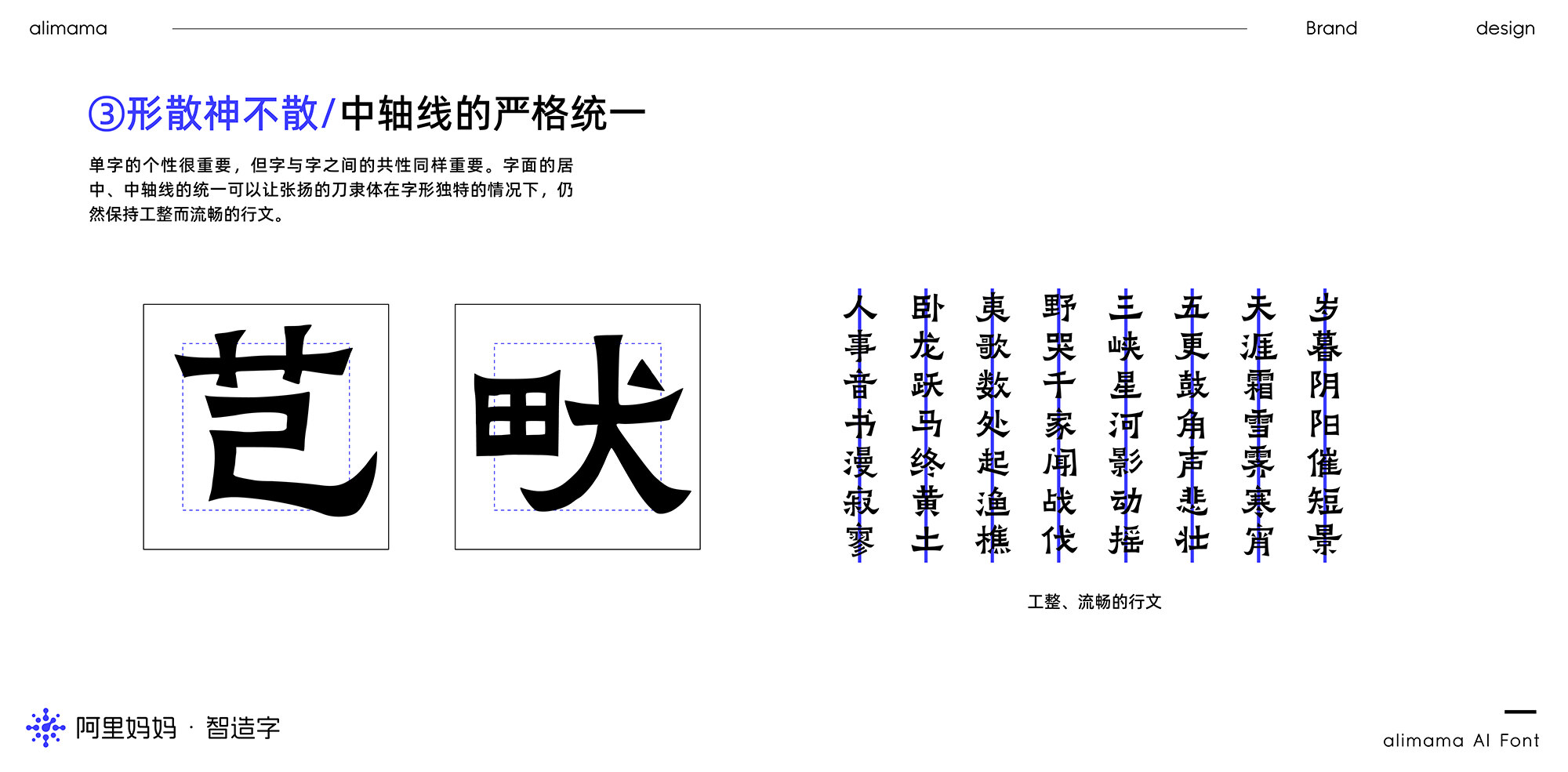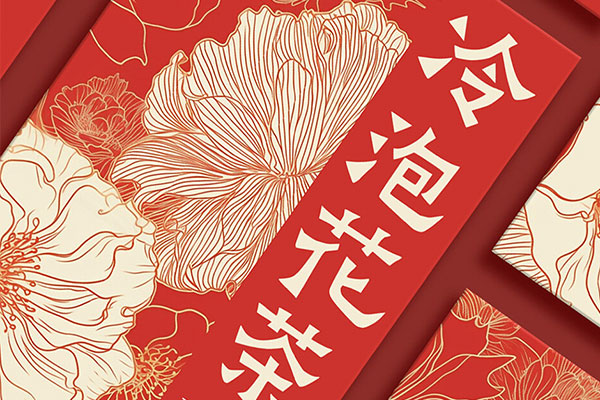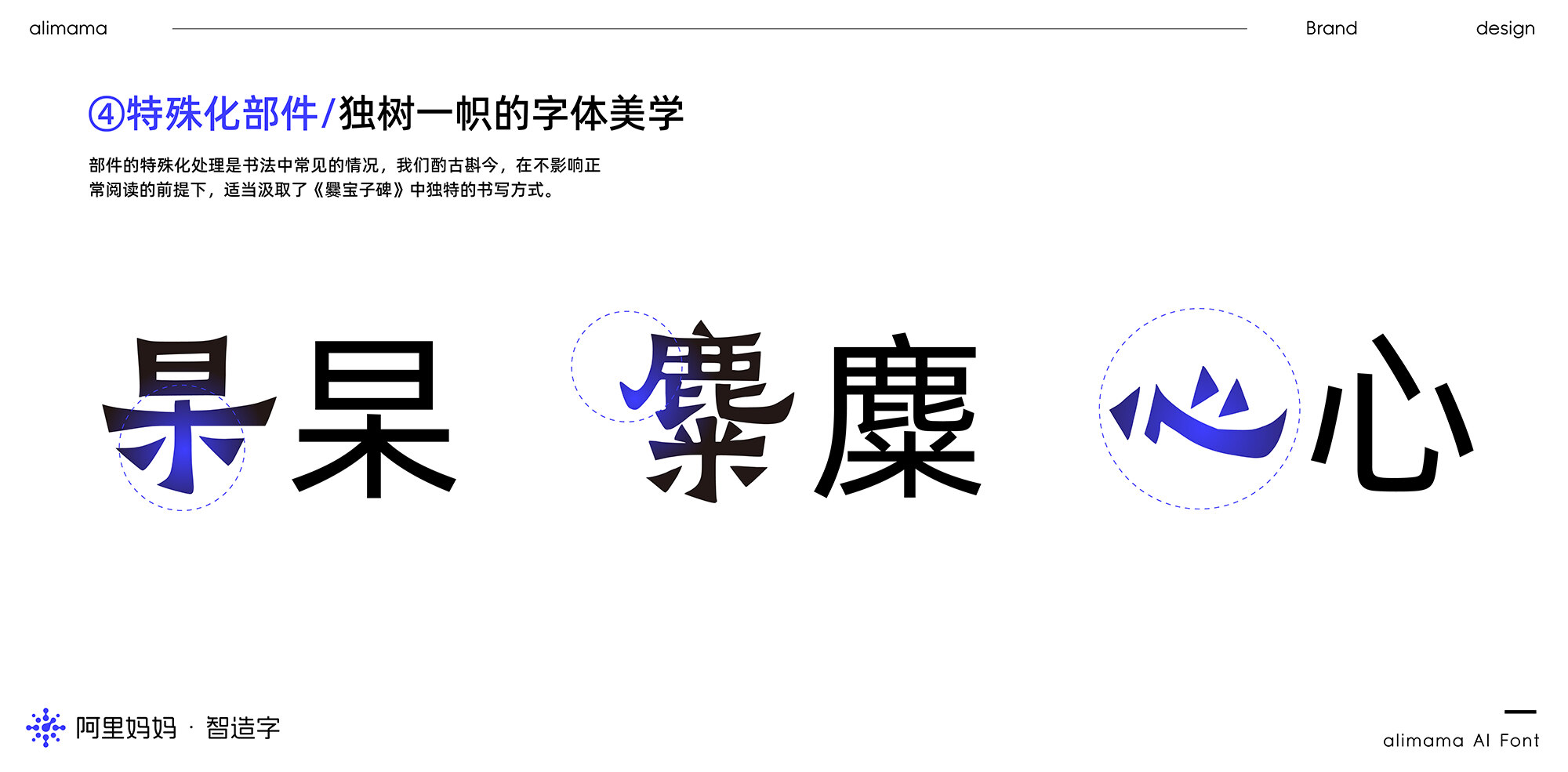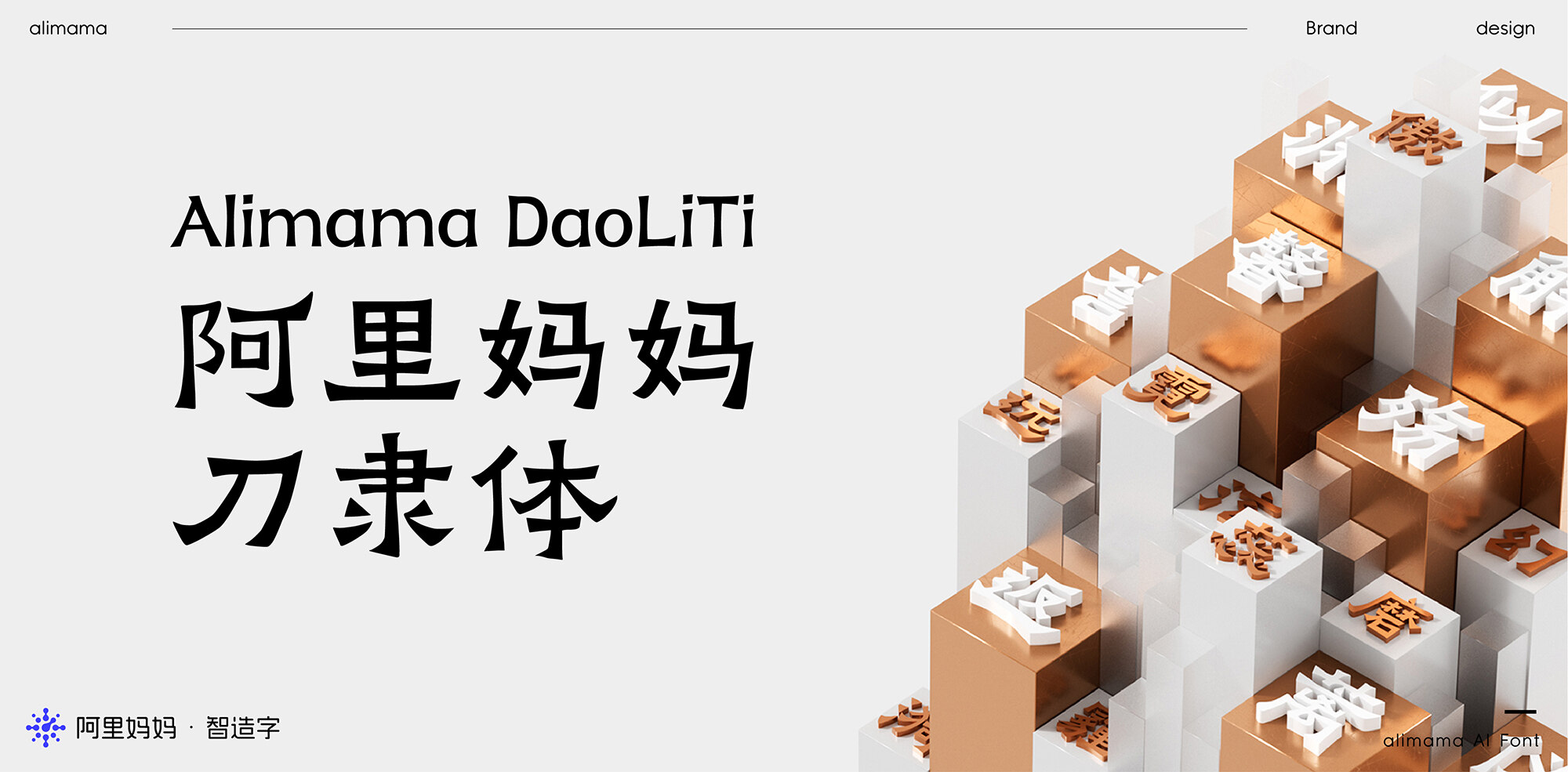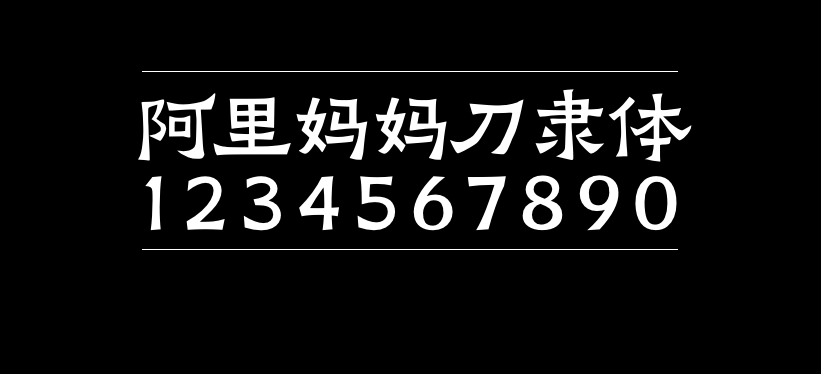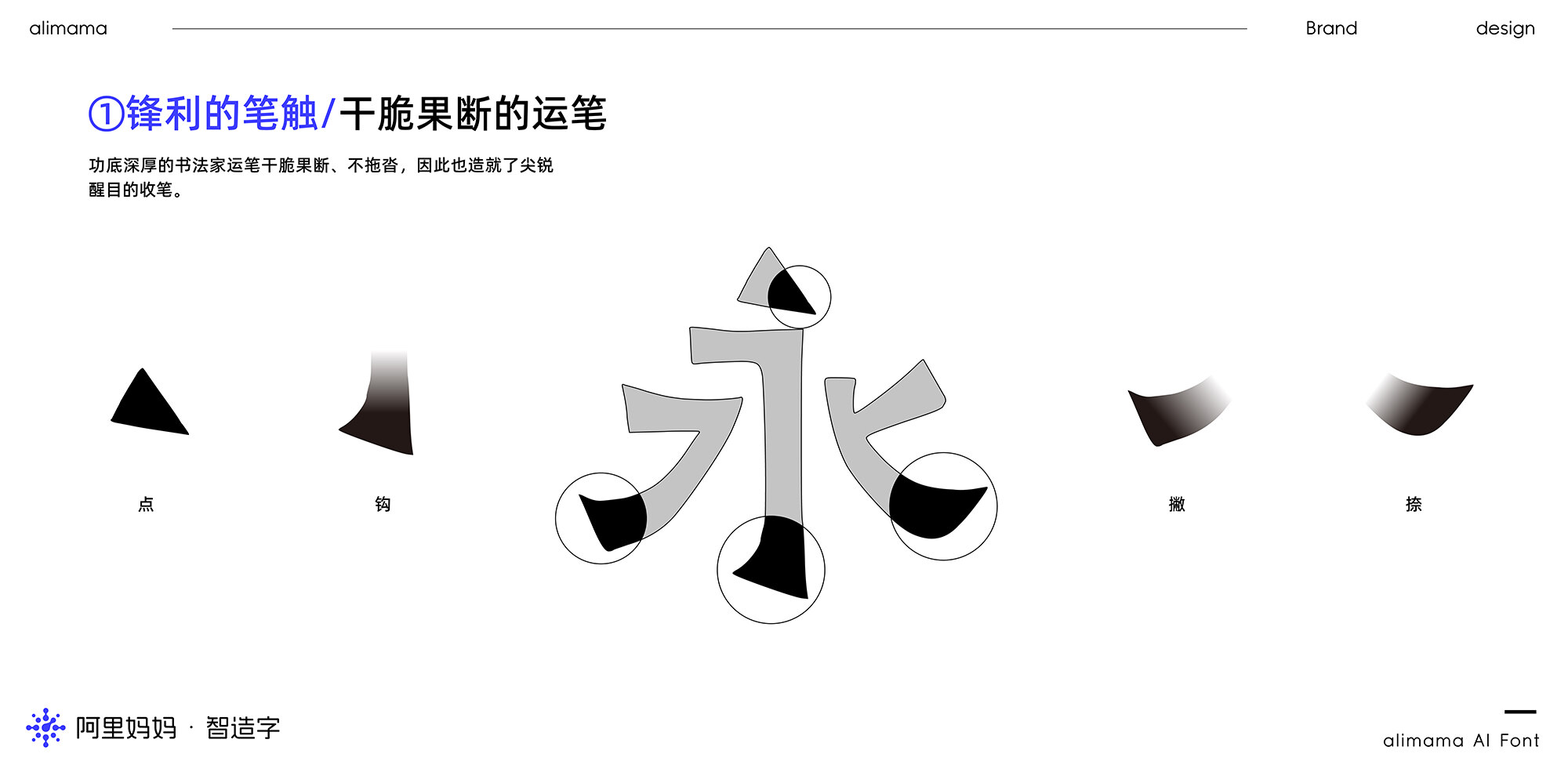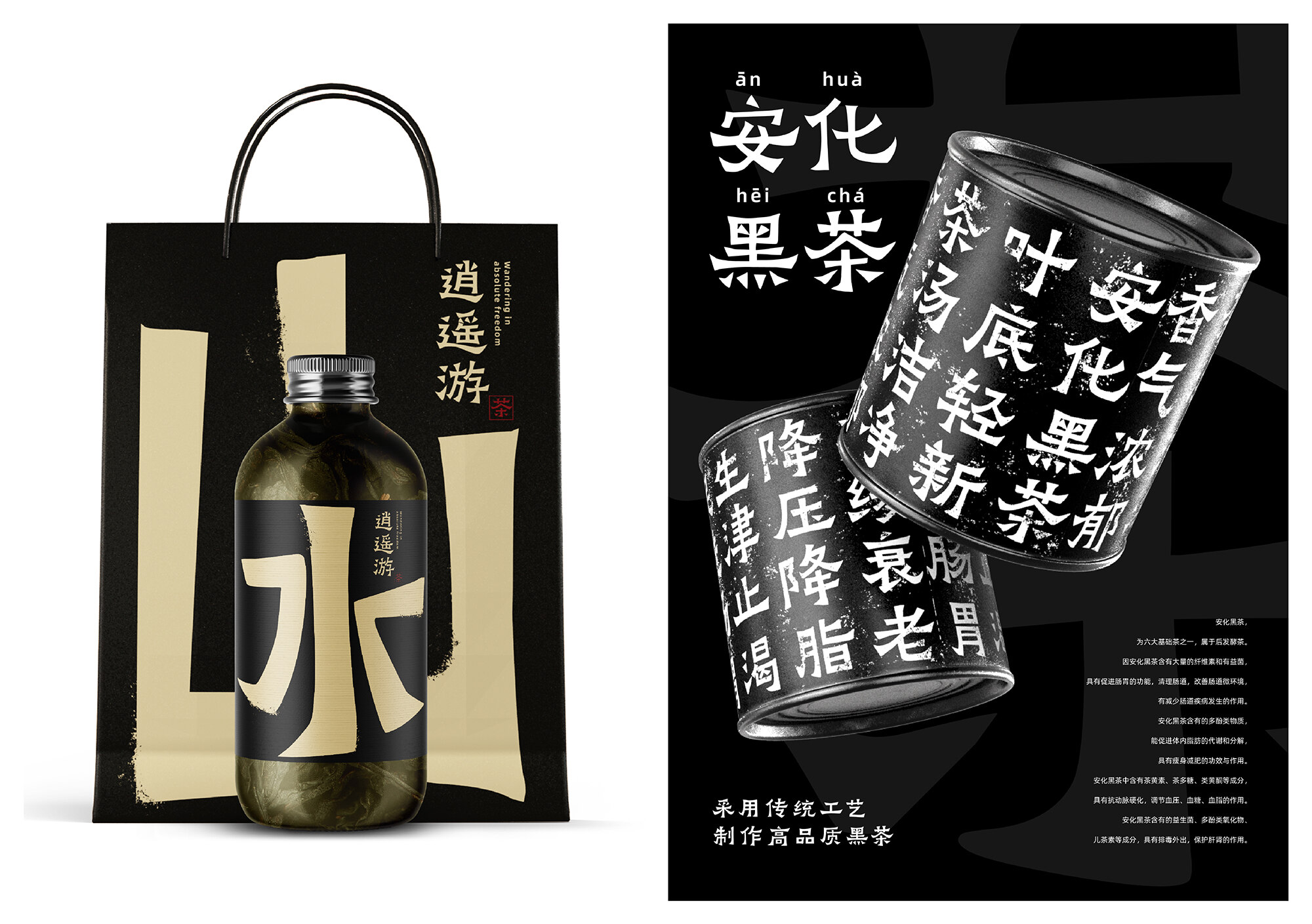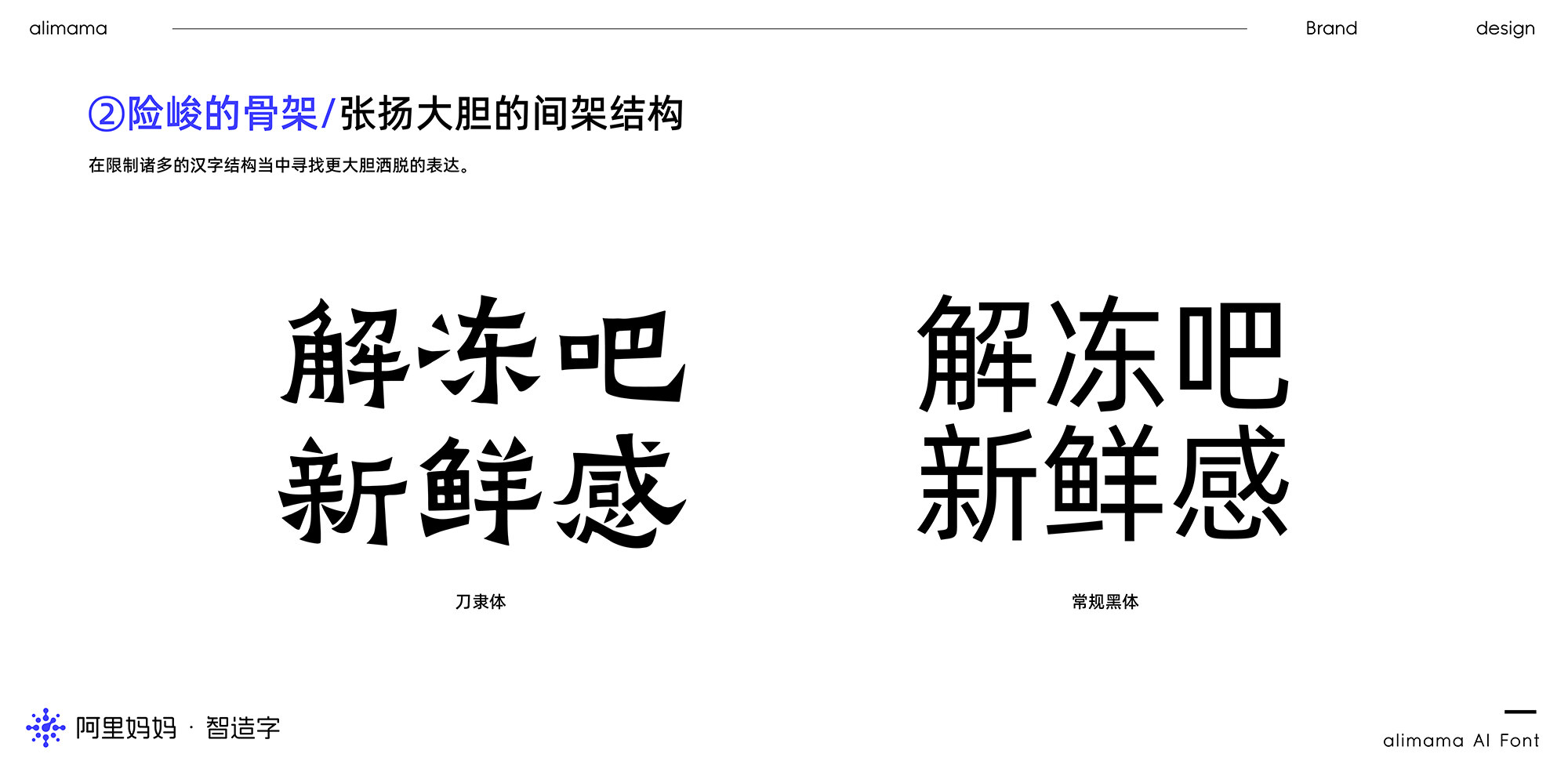
阿里妈妈刀隶体
阿里妈妈刀隶体是阿里妈妈平台推出的又一款免费商用字体,通过机器学习了爨宝子碑(全称《晋故振威将军建宁太守爨府君墓碑》)的精髓,强调了三角点折弯与横画两端“雁尾”之方强,外露锋芒,耀其精神,介于隶楷之间,保持着浓重的隶书方笔意味,给人以坚实、朴茂、稚拙、倔犟之感,打破常规常态的匀称和均衡,结构极为大胆,布白和中宫常常出人意料,看似失度,实则深得艺理,险中求正,静中欲动,动中求静。
阿里妈妈刀隶体字体效果预览